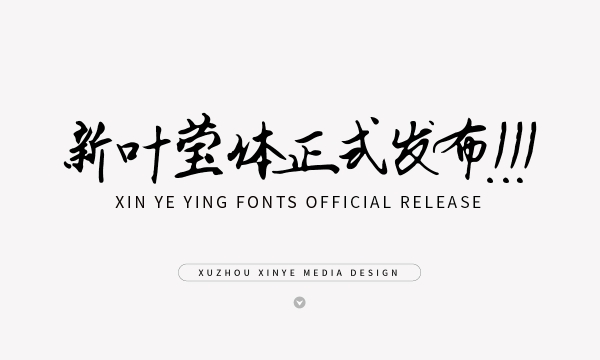
新葉瑩體字體是一款柔和而堅(jiān)毅的藝術(shù)字體,這副字體看上去溫柔而遒勁,一筆一畫(huà)之間抒寫(xiě)著一種外柔內(nèi)剛的堅(jiān)毅,橫豎撇捺之間氤氳著一絲絲的靈動(dòng),像陽(yáng)光下的玉石散發(fā)著淡淡的光彩,溫和而不刺眼,寓意為“瑩”這便是字體名字的由來(lái)了!
秀逸勻整的筆畫(huà)橫陳在每個(gè)文字間,透露著一種陰陽(yáng)和諧之美,每一個(gè)文字的筆畫(huà)都柔和平緩,避免了太過(guò)鋒利,就像做人一樣要磨平棱角處事,但也要保留自己的特色一樣。